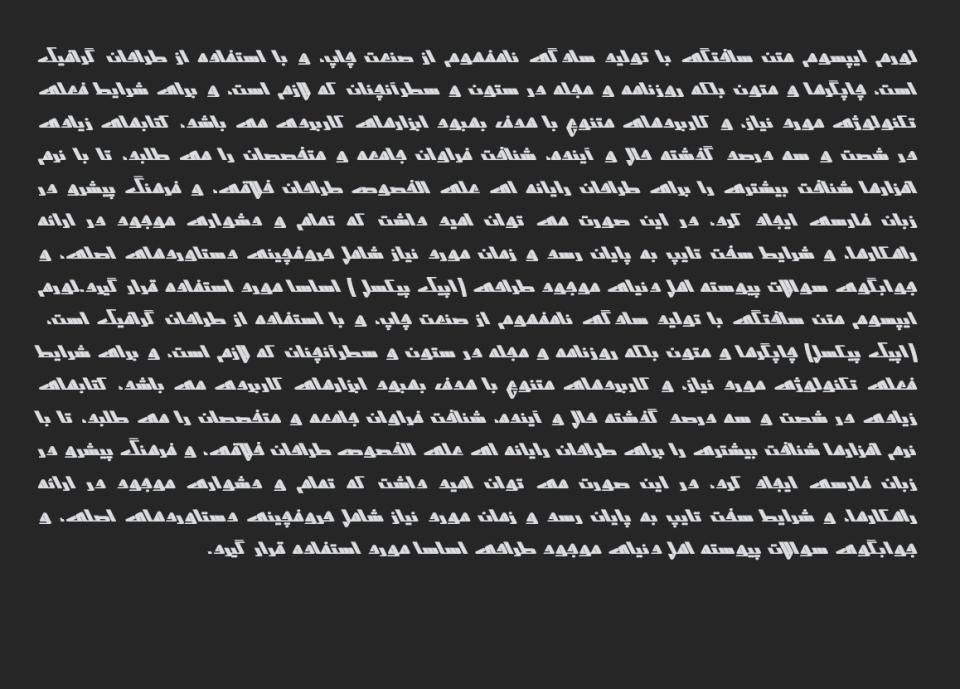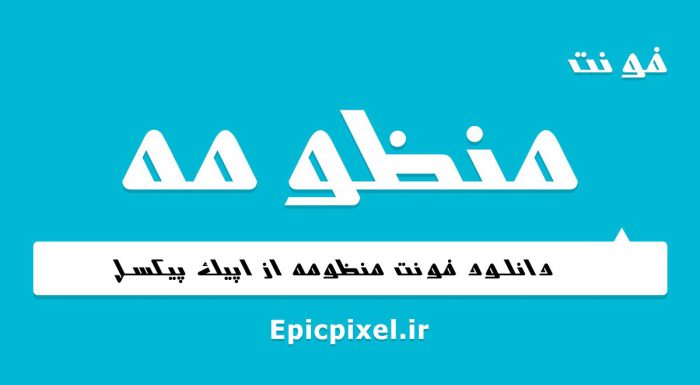
2 فونت منظومه فارسی Manzomeh
فونت منظومه، یه انتخاب خاص برای کساییه که دنبال یه ظاهر متفاوت و مدرن تو نوشته هاشون هستن. این فونت رایگانه و ویژگی های منحصربه فردی داره که اونو از بقیه فونت ها متمایز می کنه.
یکی از ویژگی های برجسته منظومه، طراحی هندسی و خطوط کج اونه که یه حس پویایی و حرکت به متن می ده، انگار که کلمات دارن به جلو حرکت می کنن. این حالت کج، شبیه به فونت های ایتالیکه، اما با یه تفاوت اساسی: منظومه یه سبک مثلثی توپر داره که به حروف یه شکل سه بعدی و چشمگیر می ده. این ترکیب خطوط کج و شکل مثلثی، یه تضاد جالب ایجاد می کنه که باعث می شه متن جذاب تر به نظر برسه.
نقطه های دایره ای که در طراحی این فونت به کار رفته، یه لطافت خاص به حروف می ده و از خشکی و جدیت اون ها کم می کنه. این نقطه ها، در کنار خطوط تیز و زوایای هندسی، یه تعادل بصری ایجاد می کنن که چشم رو خسته نمی کنه و خوانایی متن رو بالا می بره. این ویژگی برای طراحی لوگو، عناوین و پوسترهایی که نیاز به جلب توجه دارن، خیلی مفیده.
البته، باید به این نکته هم اشاره کرد که به دلیل همین طراحی خاص و هندسی، شاید فونت منظومه برای متن های طولانی و کتاب ها خیلی مناسب نباشه و بیشتر برای استفاده در عناوین کوتاه، لوگوها، پوسترها و طراحی های گرافیکی که نیاز به یه ظاهر مدرن و متفاوت دارن، توصیه می شه. به عبارتی، این فونت بیشتر جنبه ی تزئینی داره تا کاربرد متنی طولانی.
در نهایت، اگه دنبال یه فونت رایگان با ظاهری مدرن، هندسی، و متفاوت هستید که بتونه به طراحی هاتون یه جلوه ی خاص ببخشه، فونت منظومه یه انتخاب عالیه. این فونت با ترکیب خطوط کج، شکل مثلثی توپر و نقطه های دایره ای، یه تجربه ی بصری منحصربه فرد رو ارائه می ده.